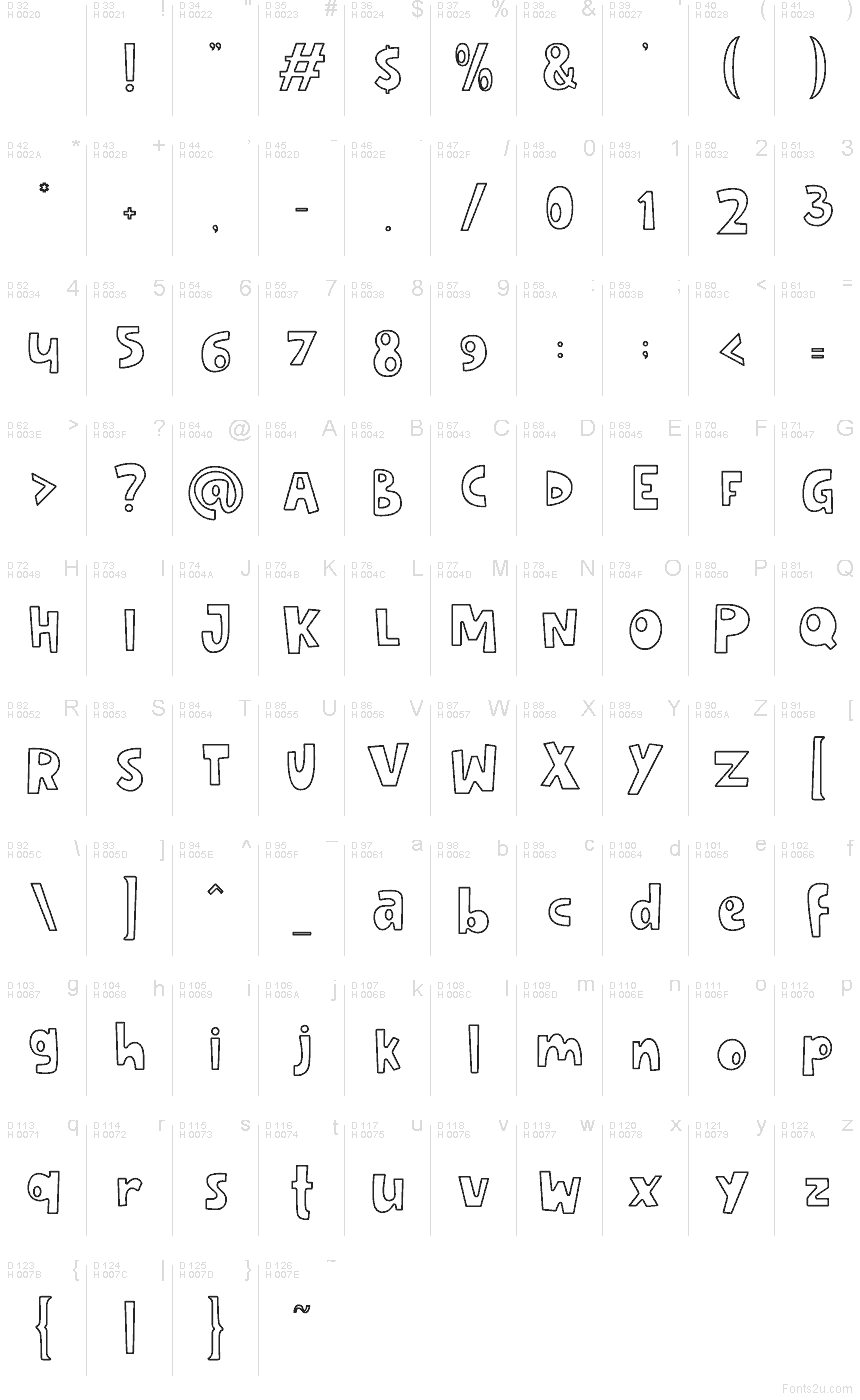
Carve Craft Four de Putracetol Studio es una fuente tipográfica gratuita con estilo de dibujos animados y un aspecto suave, hecho a mano. Sus letras parecen talladas en espuma o arcilla, con trazos exteriores gruesos, esquinas redondeadas y formas ligeramente irregulares que mantienen un aire divertido y desenfadado, huyendo de acabados demasiado perfectos.
Encaja naturalmente en marcas infantiles, empaques de juguetes, invitaciones de cumpleaños, encabezados estilo cómic y publicaciones sociales alegres donde se busca una voz amigable sin perder la naturalidad. Úsala para títulos cortos, tarjetas de presentación, diseños de pegatinas o textos de portada cuando quieras que tus letras tengan ese aspecto grande, dinámico y relajado.